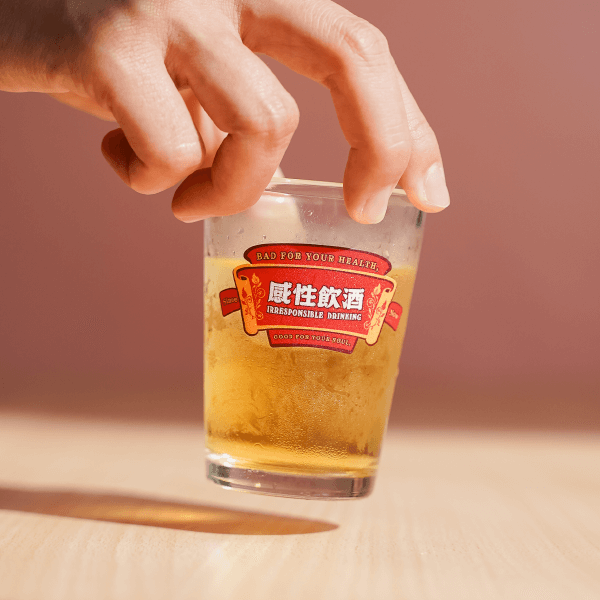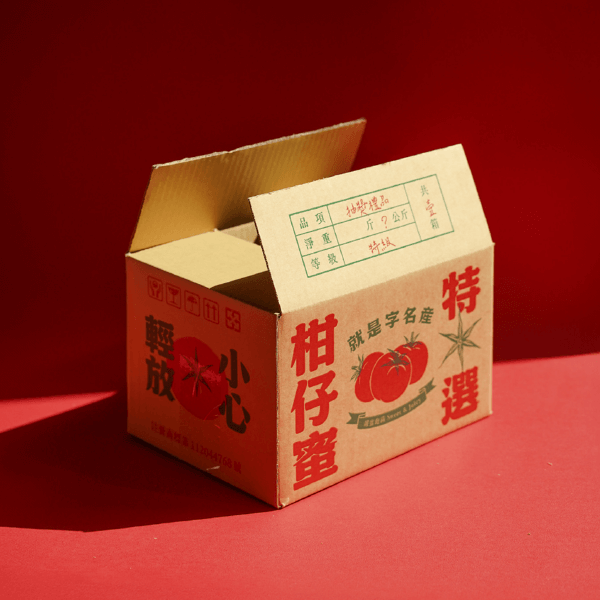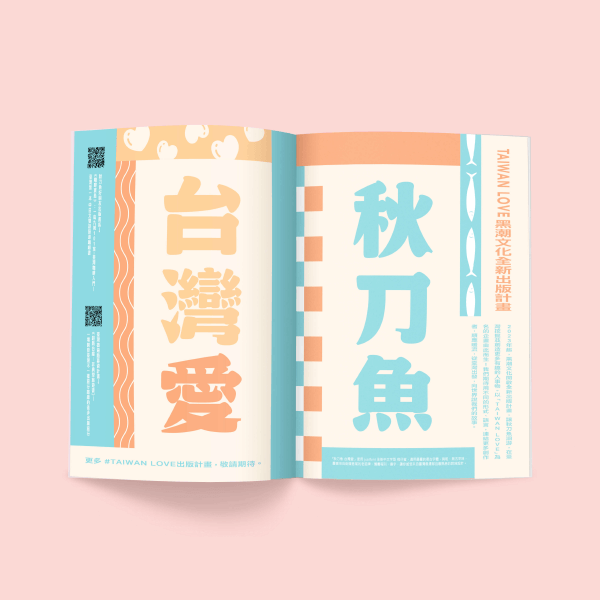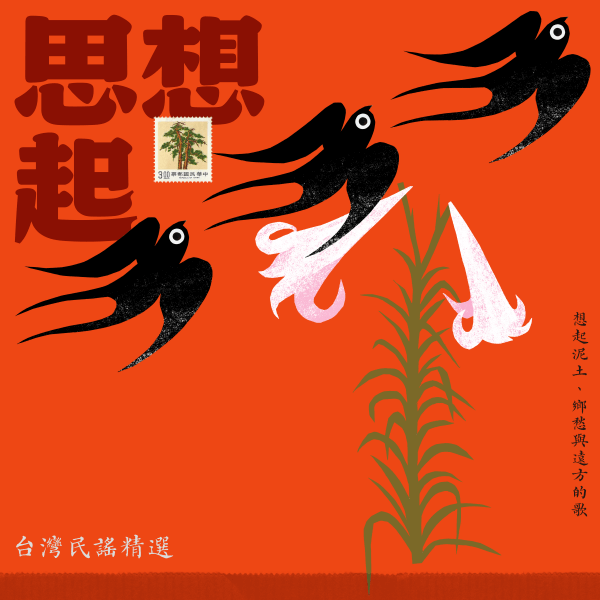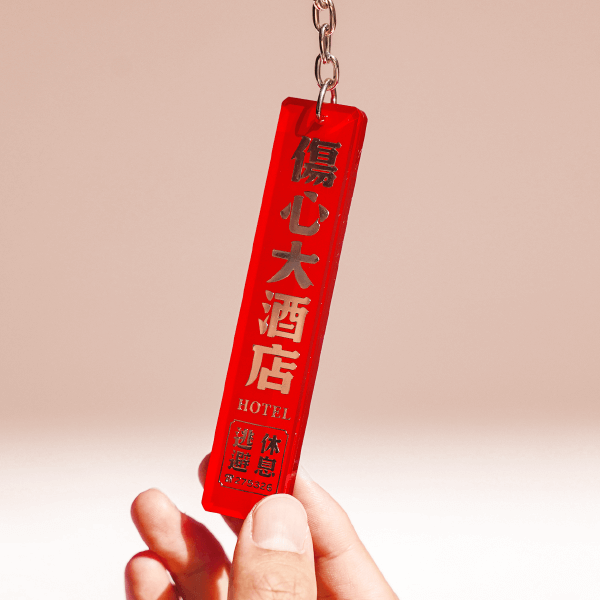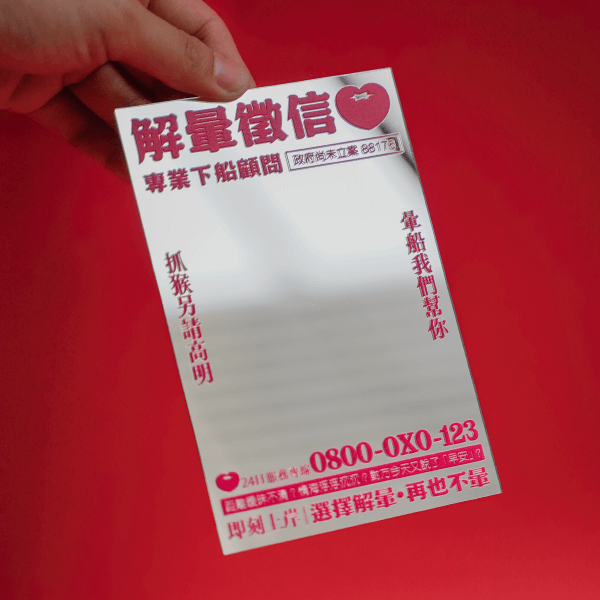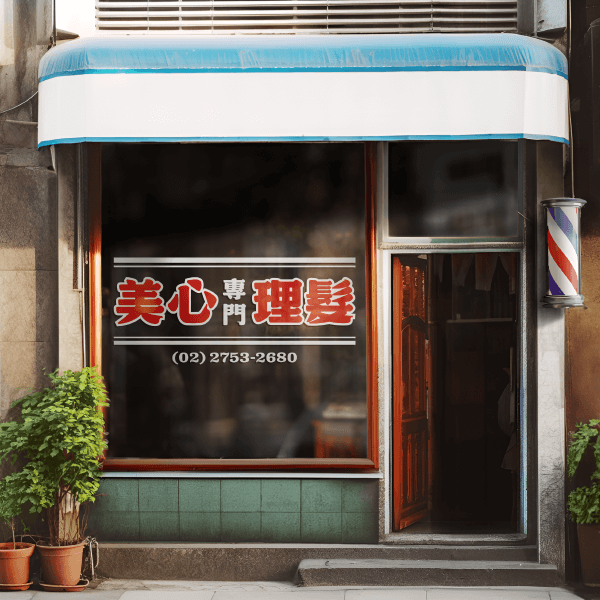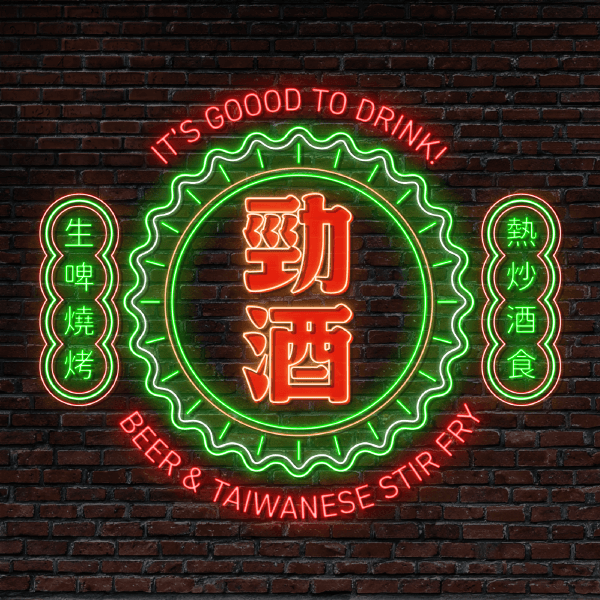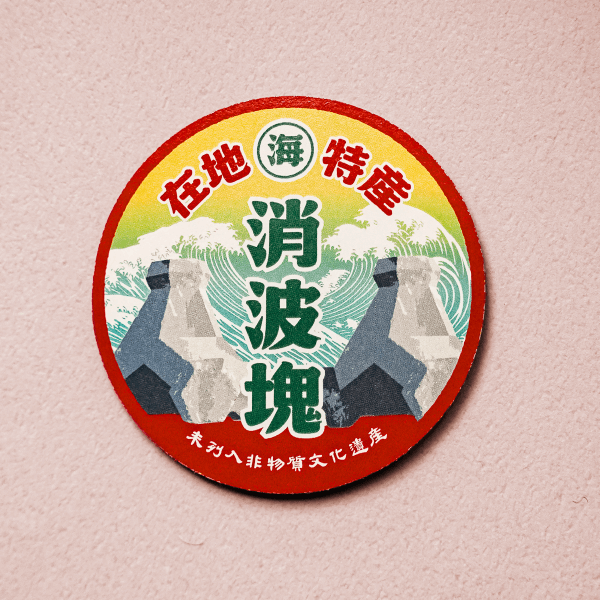
jf 柑仔蜜
敢若欠一味?Call Out 柑仔蜜!
採自回憶,手感栽培,
造型自然、飽滿,
簡單使用就能帶出台式古早味。
字型設計師
沈采柔
justfont 字型設計師,參與 justfont 從金萱以來的所有字型作品。同事表示她對許多事物有犀利而直白的見解,只是她本人對此不是很有信心。育有一犬,擅自被同事封為社犬。